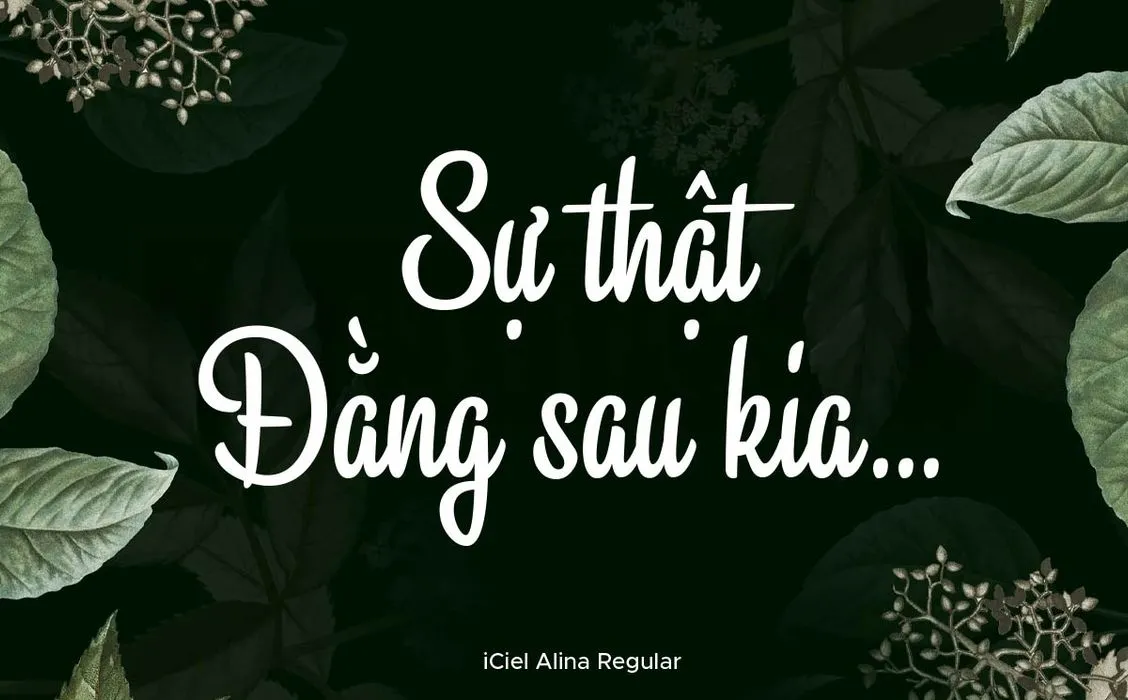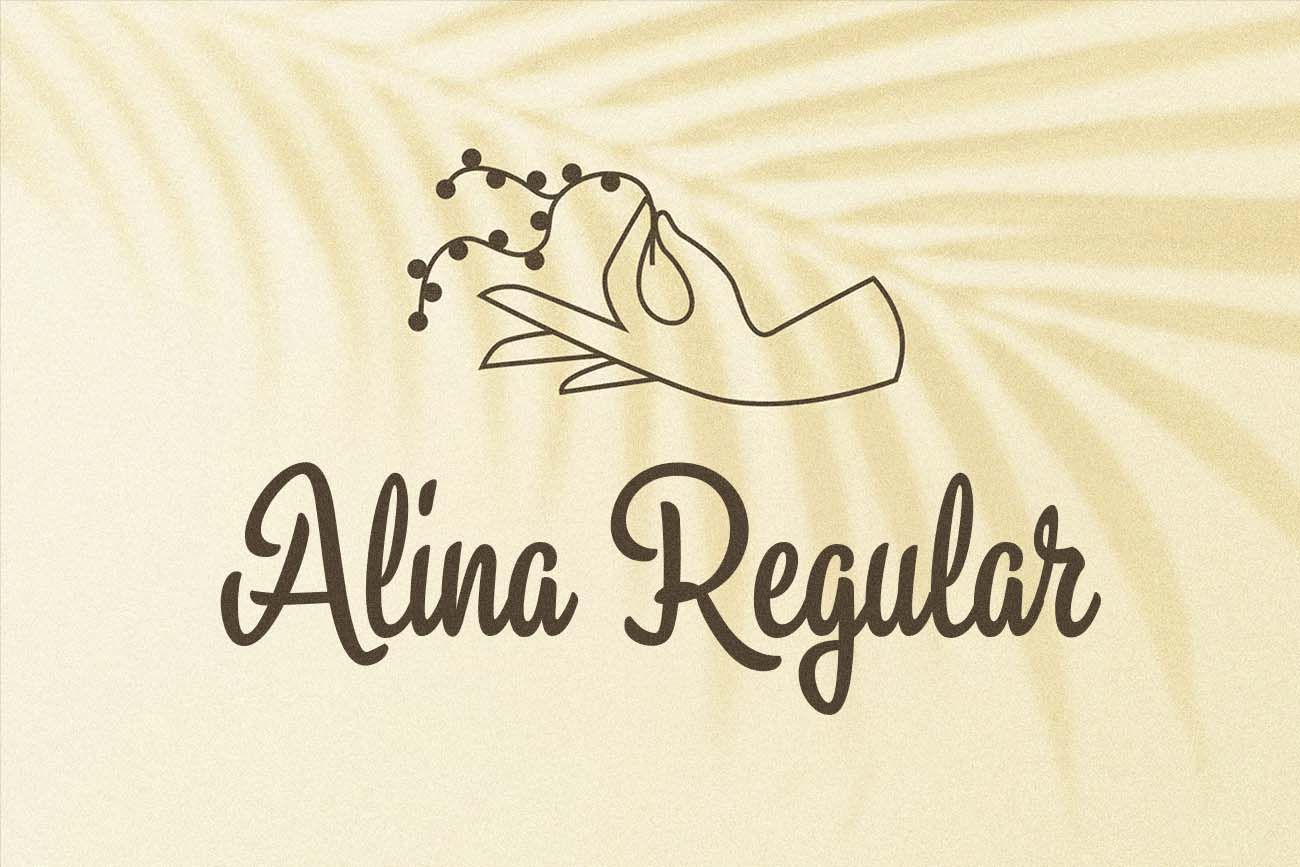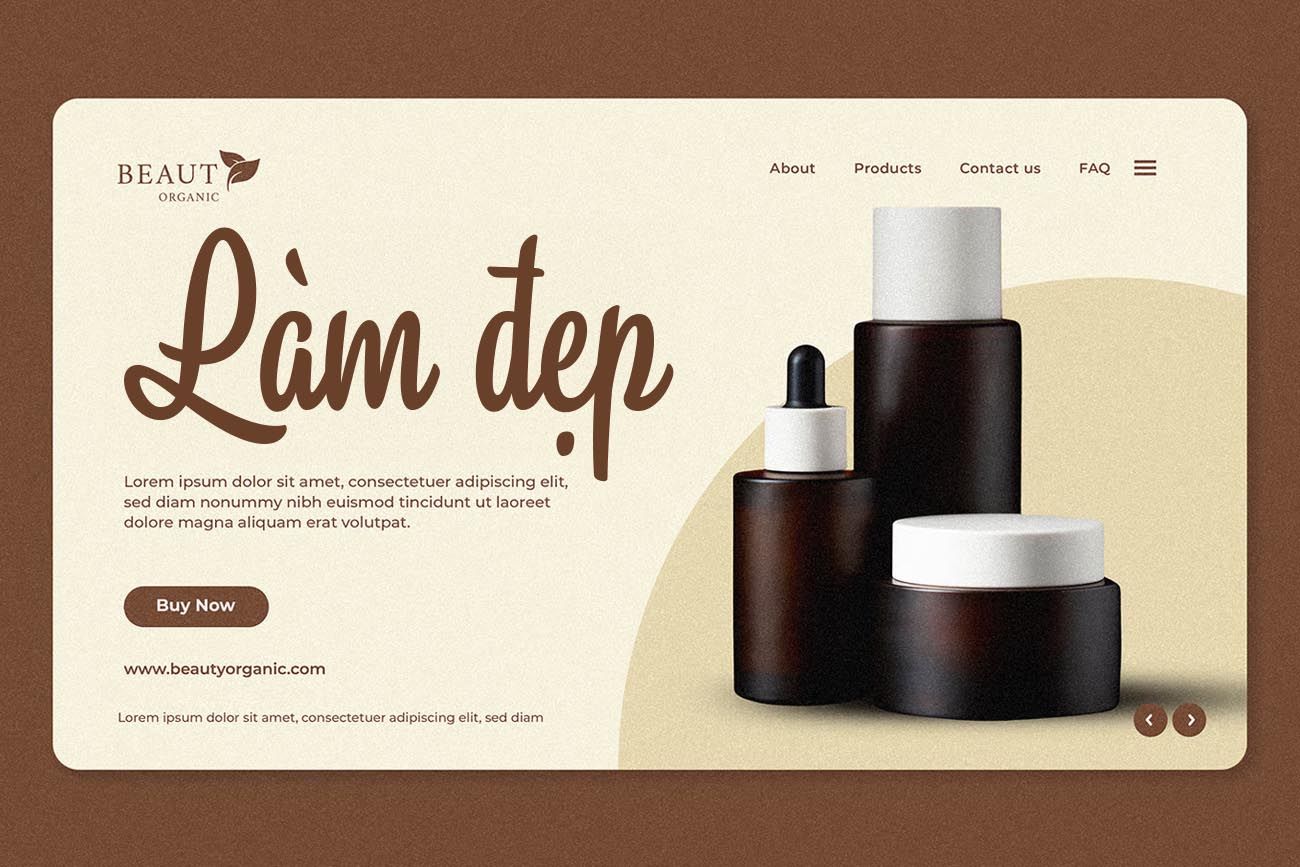
Trong thế giới thiết kế, lựa chọn font chữ phù hợp luôn là bước quan trọng để truyền tải cảm xúc và cá tính của tác phẩm. Một trong những lựa chọn đang được nhiều designer yêu thích chính là font iCiel Alina Regular. Đây là một font chữ viết tay mềm mại, uyển chuyển, mang lại sự tinh tế và thanh lịch cho bất kỳ thiết kế nào.
Bản gốc của iCiel Alina Font được sáng tạo bởi Artimasa Studio, nổi tiếng với các bộ chữ mang phong cách nghệ thuật và giàu cảm xúc. Khi được Việt hóa bởi iCiel Team, font này đã được bổ sung đầy đủ dấu tiếng Việt, giúp cộng đồng sáng tạo trong nước có thể dễ dàng ứng dụng mà không lo mất đi vẻ đẹp nguyên bản.
Font chữ iCiel Alina Regular thuộc nhóm font chữ script, với đường nét viết tay tự nhiên, kết hợp sự mềm mại và sự tinh tế của thư pháp hiện đại. Các ký tự có độ uốn cong nhẹ nhàng, tạo cảm giác gần gũi, nữ tính nhưng vẫn đủ thanh thoát để dùng trong những thiết kế sang trọng. Đây cũng là lý do font thường được xếp vào nhóm font chữ nghệ thuật được ưa chuộng.
Với phong cách bay bổng và thanh lịch, iCiel Alina Font phù hợp trong nhiều dự án khác nhau:
Thiệp cưới, thiệp mời và các ấn phẩm sự kiện.
Logo thương hiệu thời trang, mỹ phẩm hoặc quán cà phê.
Poster, typography nghệ thuật, trích dẫn truyền cảm hứng.
Bao bì sản phẩm cao cấp, thiết kế mang hơi hướng tinh tế và lãng mạn.
Nếu bạn đang tìm kiếm một font chữ viết tay vừa mềm mại vừa sang trọng, thì font iCiel Alina Regular chắc chắn là lựa chọn hoàn hảo. Với phiên bản font chữ Việt hóa hoàn chỉnh, bộ font này không chỉ giữ được vẻ đẹp gốc mà còn mang đến sự tiện lợi cho các nhà thiết kế Việt Nam trong quá trình sáng tạo.